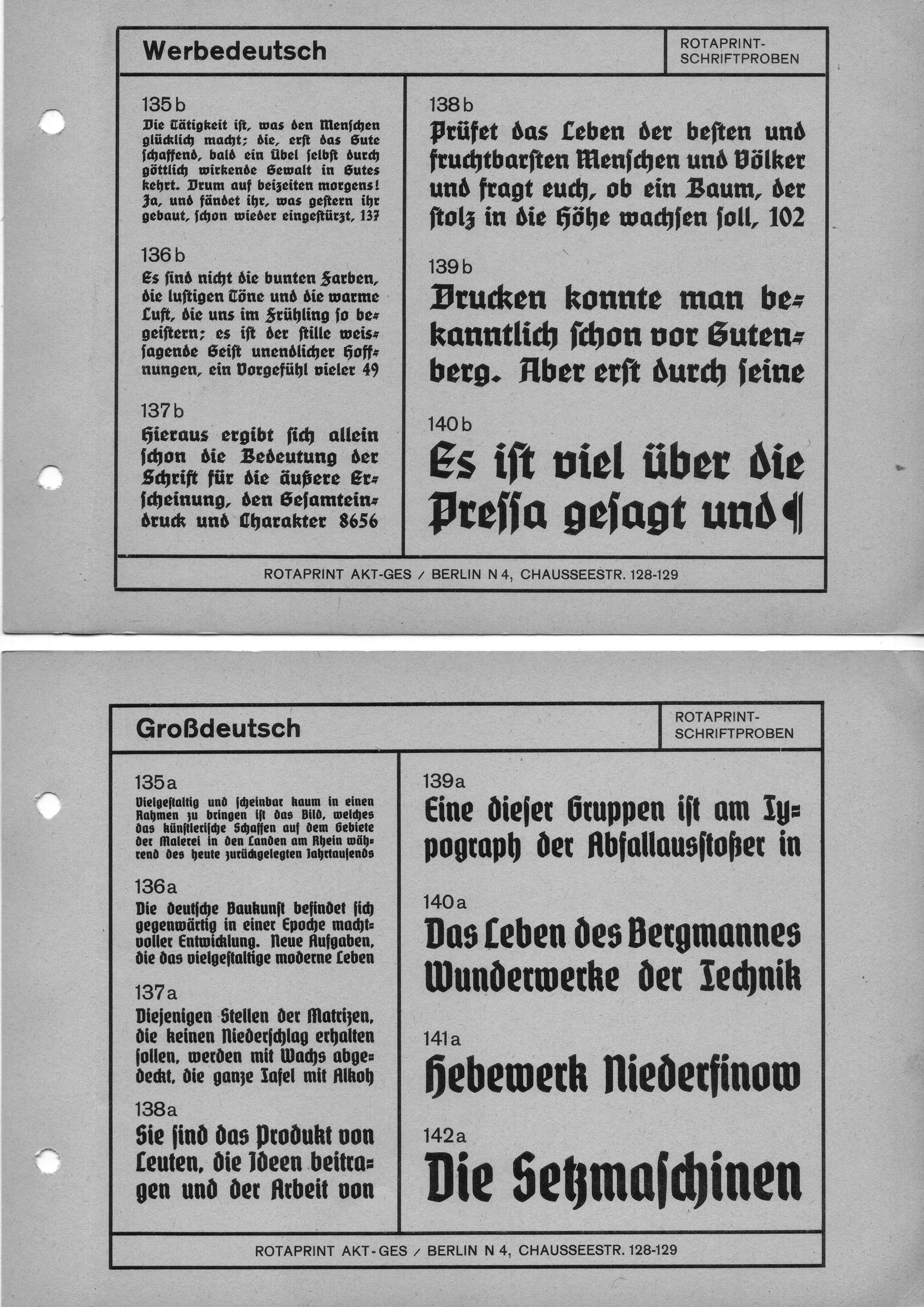
Großdeutsch/Werbedeutsch Schriftmuster
Das sind Schriftmuster von Rotaprint? Haben die außer diesen kleinen Druckmaschinen auch Schriften gemacht? Wann war denn das?
Sorry, ich schreibe gerade Müll. Die Großdeutsch ist ja von Schelter & Giesecke und stammt aus dem Jahr 1935. Pardon.